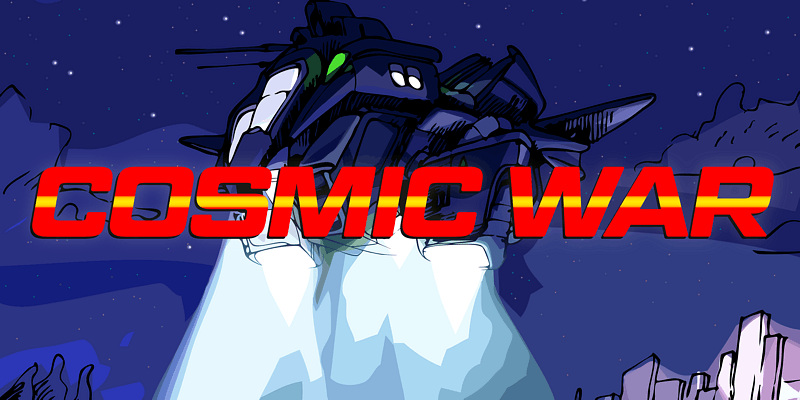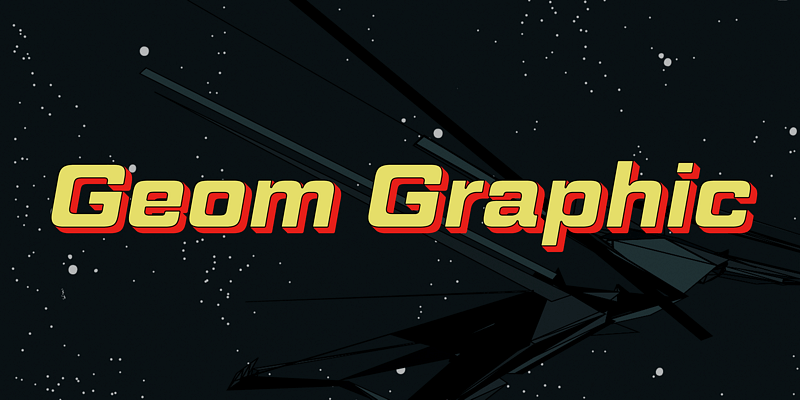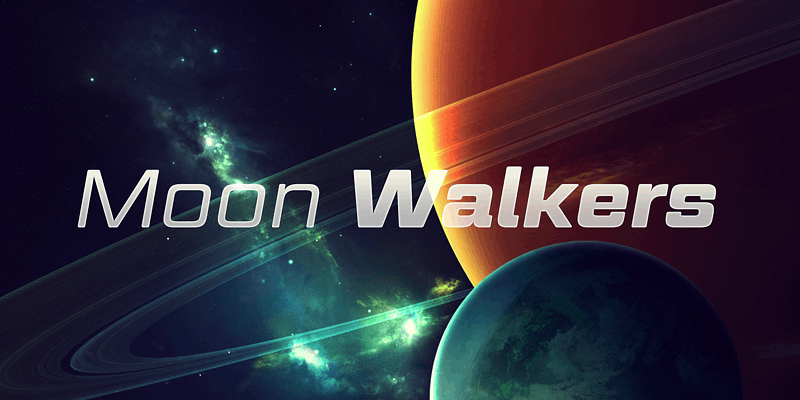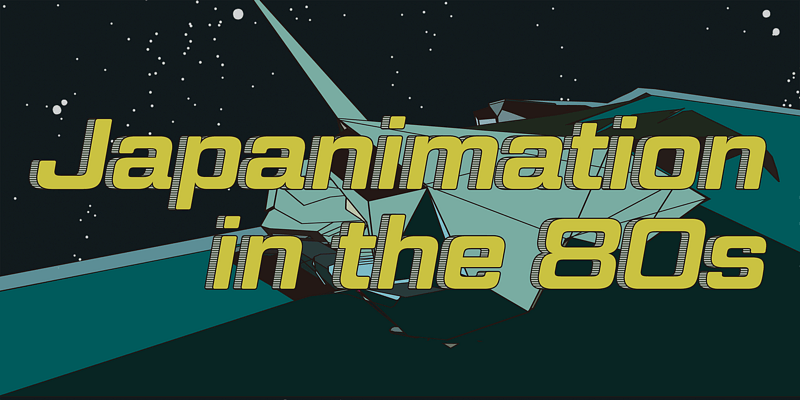
Inspirée des animations de robots japonais dans les années 80, Geom Graphic est une police géométrique carrée sans empattement pour un large éventail d’utilisations. Les formes de lettres sont dessinées légèrement arrondies pour paraître naturelles, chaudes et rétro.